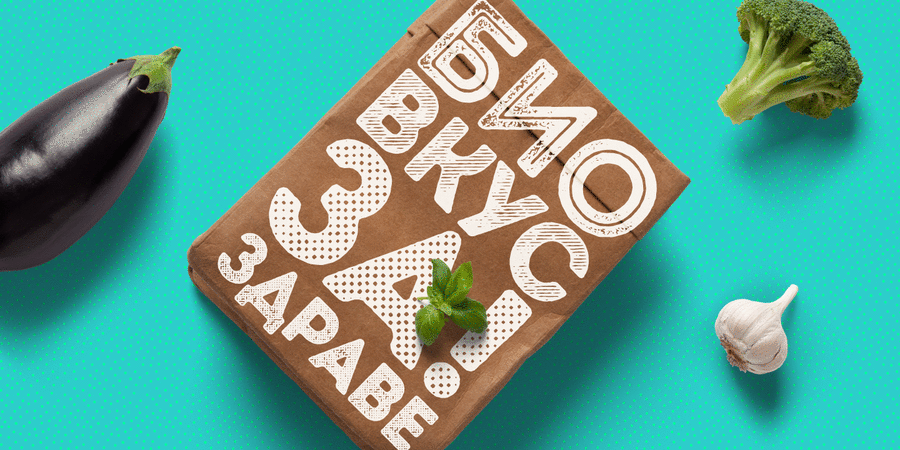
Intro Rust G Base2 (1 шрифт)
Бесплатное начертание одной из крупнейших шрифтовых систем в мире Интро Раст, включающей 214 начертаний. Это огрубленная текстурная версия известного шрифта Интро. Система Интро Раст включает 4 семейства: Intro Rust, Intro Script, Intro Head и Intro Goodies. Она может применяться для создания почти всех видов дизайнерской продукции от полиграфии до веб-дизайна. Просто используйте воображение и ваши проекты станут более живыми, благодаря шрифтам системы Интро Раст. Хотите сделать поздравительную открытку или дизайн упаковки или даже айдентику? Смело экспериментируйте с паттернами и рисунками, рукописными версиями или теми классными начертаниями с точками и получайте современный успешный дизайнерский проект. Шрифт разработан Светославом Симовым, Ани Петровой и Радомиром Тинковым в 2015 году и выпущен фирмой Фонтфабрик. http://www.fontfabric.com/intro-rust/
Асоціації з сімейством шрифтів Intro Rust G Base2Особистість і характер гарнітури:
хіпстерський, вінтажний, побутовий, грубий, помітний, яскравий, статичний, переконливий, твердий, надійний, консервативний, чесний, ветхий, старий, добротний, міцний, залізний, дерев'яний, доступний, екологічний, ефектний, зелений, натуральний, природний, теплий, ламповий, мотивуючий, оригінальний, виразний, модний, якісний, міський, суворий, крафтовий, осінній, гарячий, вогняний, запальний